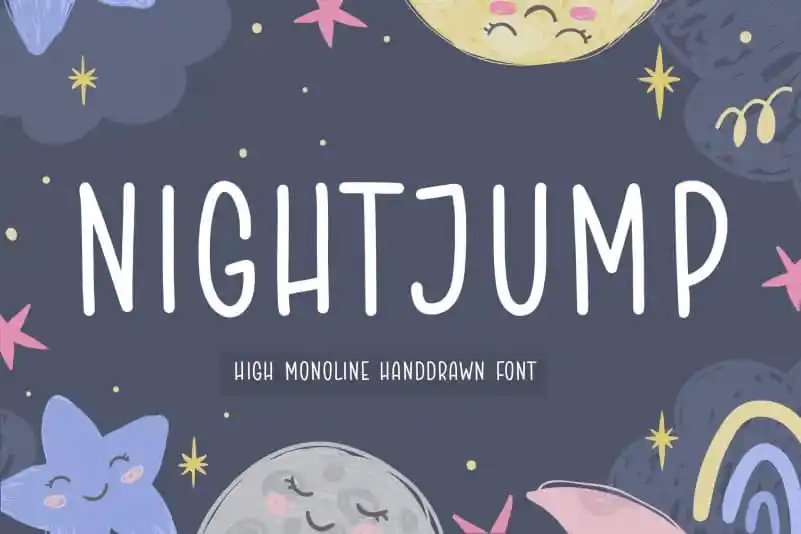
NIGHTJUMP High Monoline Handdrawn Font – Download Grátis
NIGHTJUMP é uma elegante fonte High Monoline Handdrawn que se destaca na categoria dos fonts escritos à mão. Com traços sólidos e textura natural, NIGHTJUMP oferece um estilo único para projetos variados. Perfeito tanto para identidades de marca como produtos em embalagem, também atende a necessidade criativa para megazines, redes sociais e até mesmo cartões de casamento. A sua consistência simples e moderna permite que seja usada com facilidade sobre qualquer tipo de fundo, tornando-se uma opção perfeita para quem deseja expressar os elementos mais importantes acima do background. Seja você um designer gráfico ou criador de conteúdo digital, NIGHTJUMP oferece a solução ideal para dar vida aos seus projetos digitais com estilo único e leve.